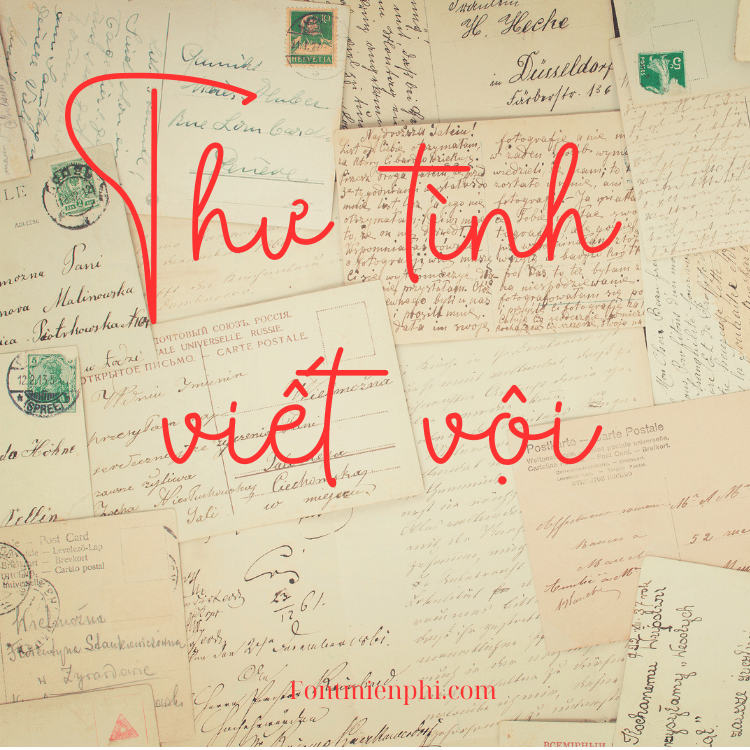
Việt hóa font Carlytte kiểu viết tay: Nét chữ thanh lịch cho thiết kế Việt
Giới thiệu về Việt hóa font Carlytte kiểu viết tay
Trong thế giới đồ họa hiện đại, việc lựa chọn một Font Miễn Phí chất lượng là yếu tố then chốt để tạo nên sự khác biệt. Việt hóa font Carlytte kiểu viết tay là một trong những bộ phông chữ được yêu thích nhất nhờ vào những đường nét thanh mảnh, bay bổng và đầy cá tính. Carlytte không chỉ đơn thuần là một bộ chữ số hóa, mà nó còn mang trong mình linh hồn của những nét bút lông mềm mại, tạo cảm giác gần gũi nhưng không kém phần sang trọng. Đối với các bạn học sinh và giáo viên, việc sử dụng bộ font này sẽ giúp các bài thuyết trình hay tài liệu học tập trở nên sinh động và lôi cuốn hơn bao giờ hết.
Đặc điểm nổi bật của font Carlytte việt hóa
Vẻ đẹp mềm mại và ứng dụng đa dạng
Bộ Việt hóa font Carlytte kiểu viết tay sở hữu các ký tự được trau chuốt tỉ mỉ, giúp văn bản tiếng Việt giữ được sự tự nhiên mà không bị lỗi dấu hay chồng chéo. Với cấu trúc các nét nối tinh tế, Carlytte cực kỳ phù hợp cho các thiết kế thiệp mời, bìa sổ tay hoặc các dự án nghệ thuật tại trường học. Khả năng hiển thị rõ nét trên cả màn hình máy tính và bản in giúp người dùng hoàn toàn yên tâm về chất lượng trình bày.
Tối ưu hóa cho người dùng Việt Nam